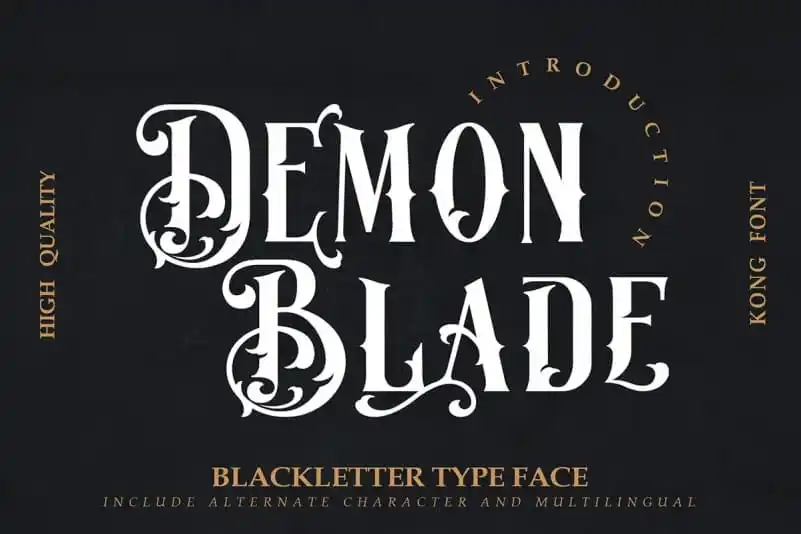
Demon Blade Blackletter Font
Introduzimos a Demon Blade Blackletter Font, inspirada nos antigos escritos ocidentais. Esta elegante família de caracteres mantém apenas letras maiúsculas e inclui símbolos multilíngues, criando um visual único que é perfeito para design de logotipos vintage, cabeçalhos ou embalagens. Suas formas robustas e detalhes distintivos a tornam uma escolha ideal para aplicativos variados como embalagens, capas de revistas e álbuns, editoriais, headlines, logomarcas, convites, marcações e muito mais. Engajue-se neste design visual fascinante e experimente as inúmeras possibilidades criativas que a Demon Blade Blackletter Font oferece para o seu próximo projeto gráfico.